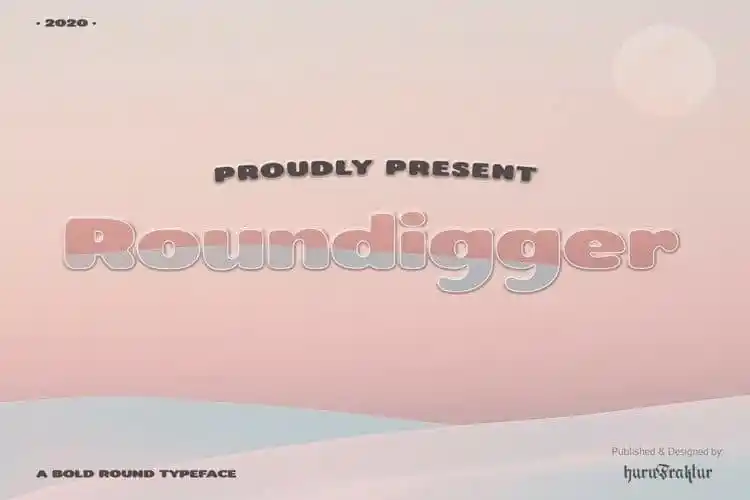
Roundigger Sans Serif Font – Fonte Grátis
Roundigger Sans Serif Font
A Roundigger Sans Serif Font é uma excelente escolha para designers que buscam um tipo sem serif com um aspecto vintage, mas atual. Esta fonte é desenvolvida pelo designer Hurufraktur e oferece linhas retas e geométricas repletas de ângulos arredondados, criando um visual agradavelmente suave para logomarcas e outros projetos gráficos. Ideal para criações em impressão, a Roundigger é versátil o suficiente para atender a uma variedade de necessidades de design. Seu uso permite que você crie designs vivos e estéticamente inspiradores, apenas com sua imaginação e um conjunto de ferramentas gráficas. Escolha esta fonte para seu próximo projeto visual, onde desejam-se ambientes profissionais agradáveis ou modernamente vintage.